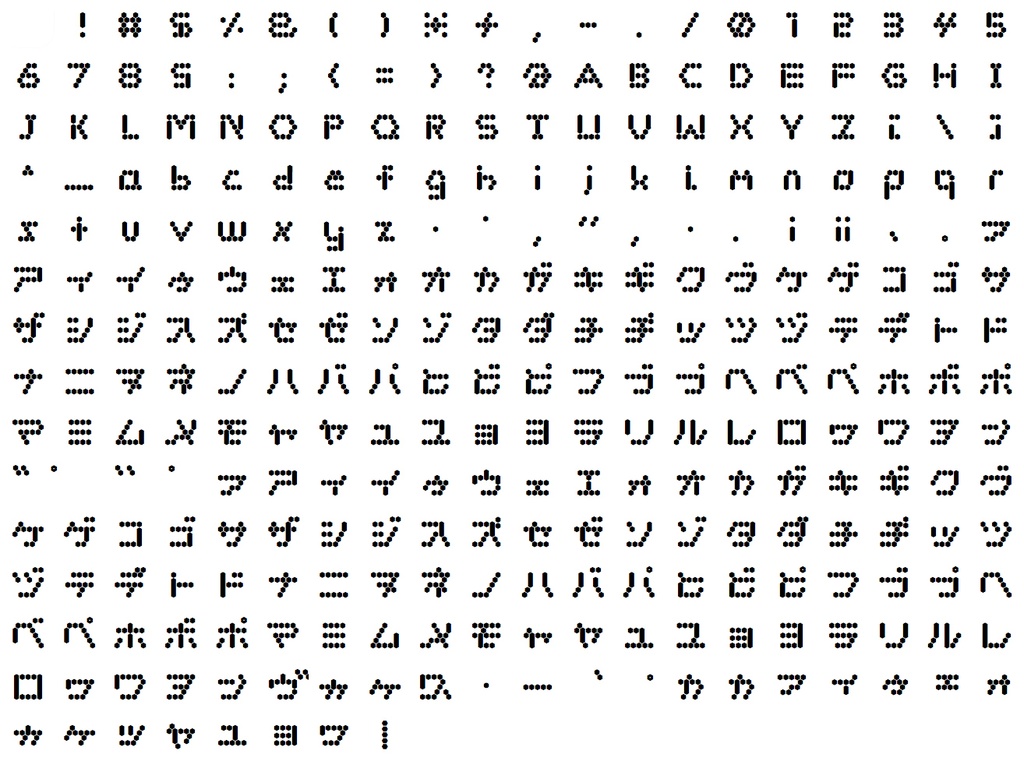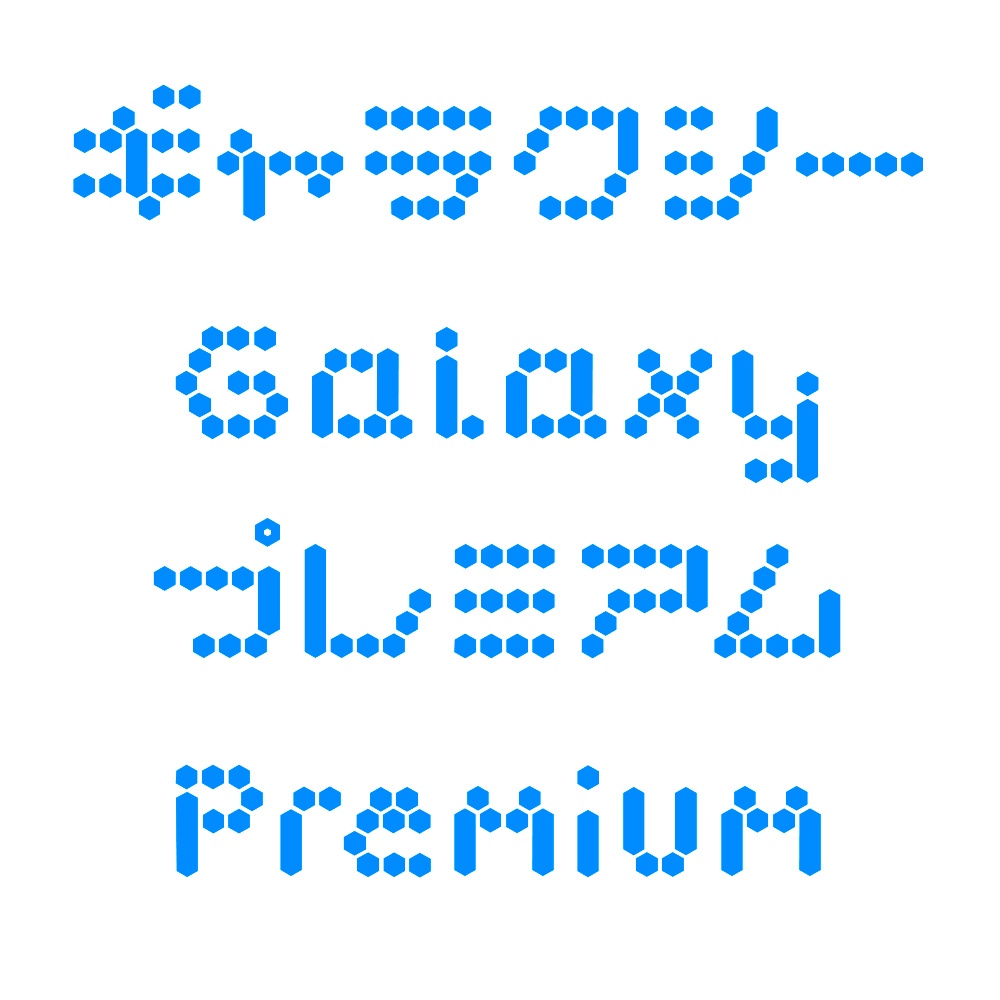
ハニークリスタルFONT
ハニークリスタルFONT 六角形のドットの基本にしたロゴ向けのフォントです。キラキラ、未来っぽい表現など楽しく使ってください。 動作環境 Mac:システム/OS X対応(10.x)〜最新のOS X Windows:OS/日本語版Windows2000、XP、VISTA、Windows7〜11以降 フォント形式:OpenTypeフォント 収録文字数について アルファベット、カタカナのみの書体になります。 安心して使えるロイヤリティフリーの書体 あらゆる商用・デザイン用途(印刷物・ゲーム・アプリ・映像・動画・ロゴ・同人作品)に使用できる、商用申請の必要のないロイヤリティフリーの書体になります。文字の加工・変形も可能です。ご安心ください。 個性的なデザインに注目した日本語フォントのダウンロード販売。安心して使える商用利用可のオリジナルフォントです。